Quando costruisci il tuo sito web, ci sono molte cose che devi pianificare. Queste possono variare da compiti tecnici a impegni più creativi come la selezione di uno schema di colori e, in questo caso, la scelta dei font giusti.
Ma, con le migliaia di font disponibili, probabilmente ti starai chiedendo quale sia il migliore da utilizzare per il tuo sito web. Bene, sei fortunato, perché siamo qui per aiutarti a fare proprio questo.
Data l’ampia varietà di font, è stato difficile limitare questa selezione a soli 15 font, ma abbiamo raccolto il meglio del meglio tra cui scegliere.
1. Cambria
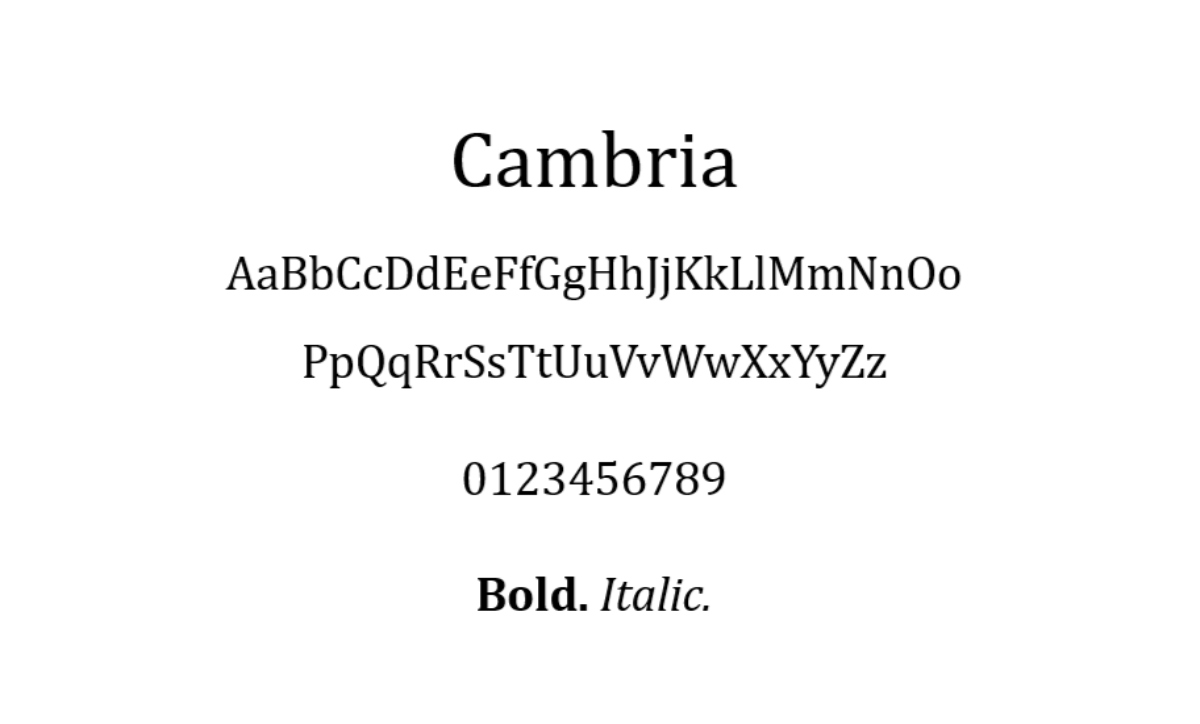
Con spaziatura e proporzioni molto costanti, Cambria è stato creato per un’eccellente lettura su schermo, anche quando visualizzato in piccole dimensioni. Troverai quattro diversi stili di questo font: regolare, grassetto, corsivo e corsivo grassetto.
Grazie ai graziati orizzontali in questo font, che enfatizzano fortemente le estremità di ogni tratto, è molto leggibile.
La versatilità di questo font è un’altra cosa che noterai. Il font può essere utilizzato per il corpo del testo, titoli e intestazioni combinando i suoi vari stili.
2. Arial
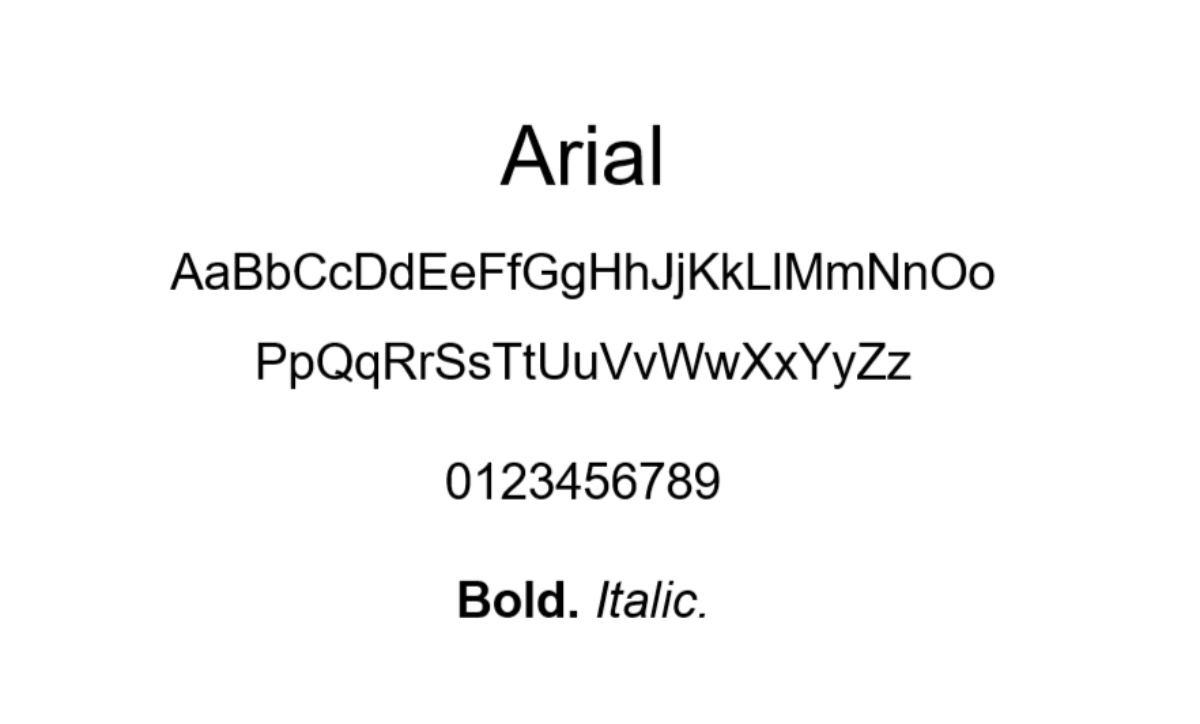
Con un’estetica moderna, Arial è un font sans-serif polivalente. La costruzione spessa e solida di ogni lettera crea un aspetto semplice e moderno.
Poiché Arial può essere letto a qualsiasi dimensione, è diventato un font standard per lo schermo. È persino diventato il font predefinito per Google Docs. Inoltre, questo font è ampiamente utilizzato in materiali stampati come pubblicità e giornali.
Arial è un’opzione fantastica se non stai cercando qualcosa di grande o elegante e vuoi semplicemente optare per un font tradizionale che funzionerà bene sulla maggior parte dei siti web.
3. Verdana
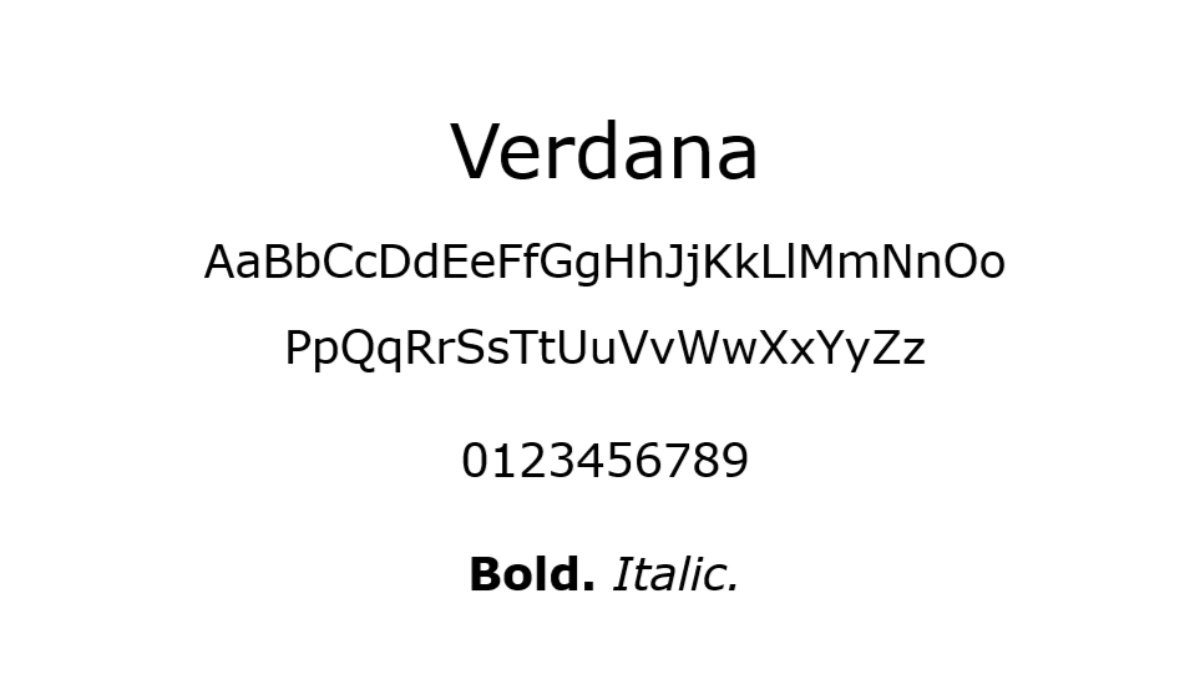
Verdana è un ottimo font per lo schermo perché può essere letto in piccole dimensioni e su schermi con bassa risoluzione. Questo è principalmente dovuto alla spaziatura ampia e alla larghezza dei caratteri.
Questo carattere non è solo per l’uso nella tipografia su schermo, però. Ad esempio, la nota azienda di mobili IKEA utilizza Verdana sia per i suoi cataloghi stampati che per il sito web.
Se stai cercando un font HTML con eccellente leggibilità, questo font è un’opzione fantastica
4. Perpetua
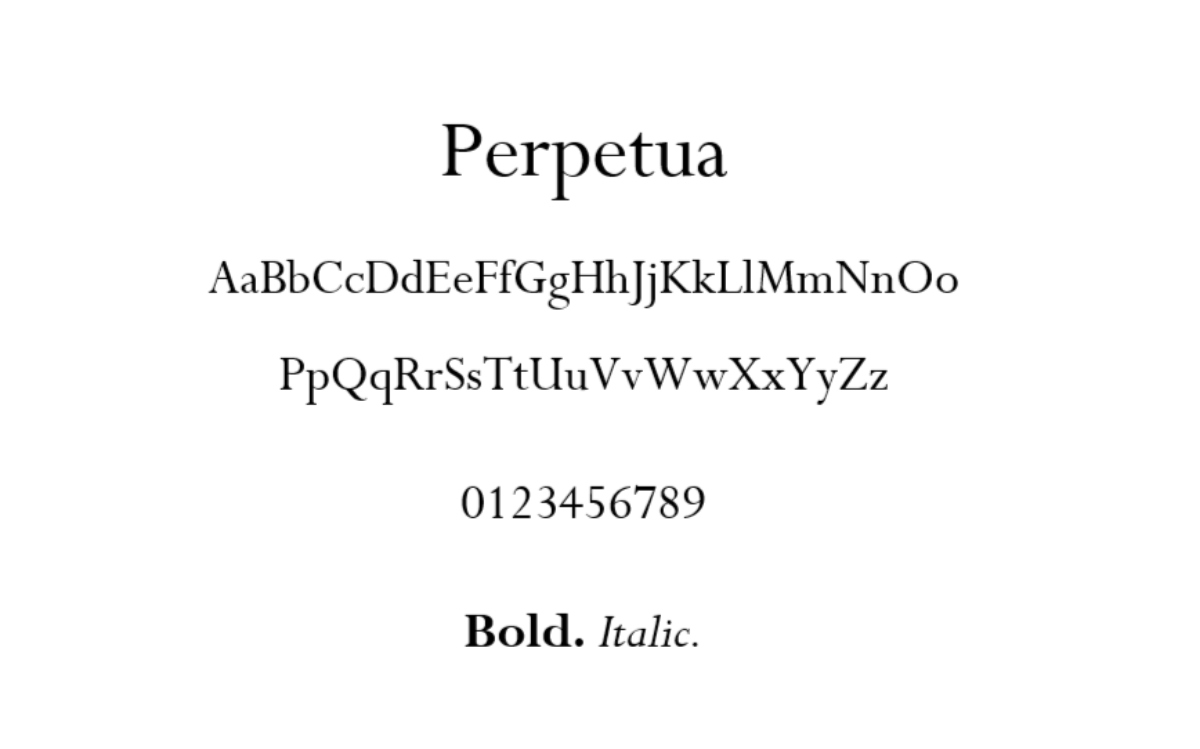
Perpetua è formale, senza tempo e raffinato. Uno scultore inglese che si è ispirato alle iscrizioni commemorative e ai monumenti ha sviluppato il font per la British Monotype Corporation.
Ancora di più, le qualità di questo font hanno ispirato l’Università della Pennsylvania e Penguin Classics a utilizzare Perpetua nelle loro pubblicazioni.
Nel complesso, questo font è molto utile per pagine e siti web educativi o informativi.
5. Brush Script
Se stai cercando qualcosa di informale e casual, allora Brush Script è un ottimo font script dall’aspetto moderno. Ha un design calligrafico basato sui metodi di scrittura. Ecco perché Brush Script MT è un font display stupendo ma leggibile per il tuo sito web.
Inoltre, questo font funziona bene per newsletter pop-up e landing page sui siti web. Considerando la natura dei suoi componenti, è meglio utilizzare questo font con parsimonia e in grandi dimensioni.
6. Monaco
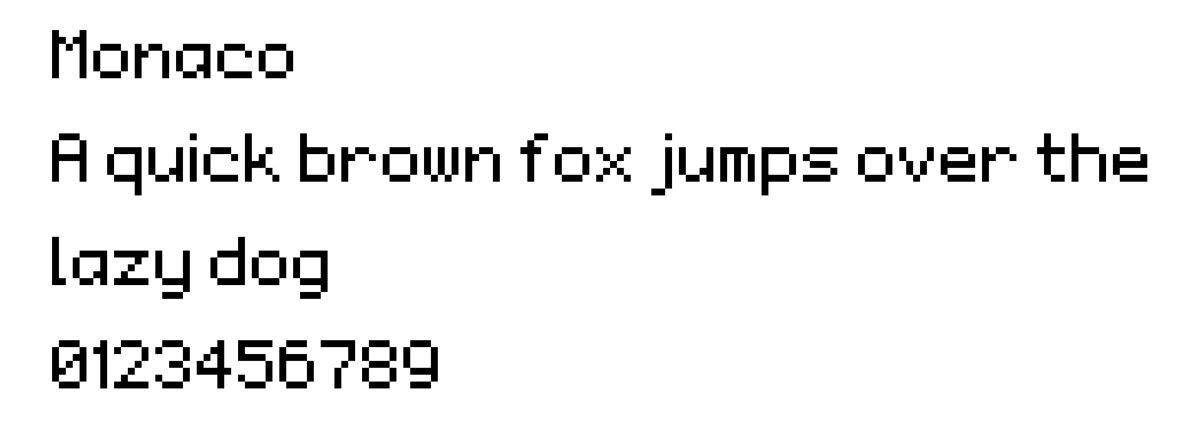
Se stai cercando un font utilizzato dalle applicazioni Xcode e Terminal su macOS X, allora Monaco è quello che stai cercando. Presenta un design pixelato ed enfatizzato che lo fa risaltare.
Monaco appare al meglio quando utilizzato come testo decorativo su layout di siti web dedicati alla codifica o al gaming grazie al suo design unico.
7. Candara
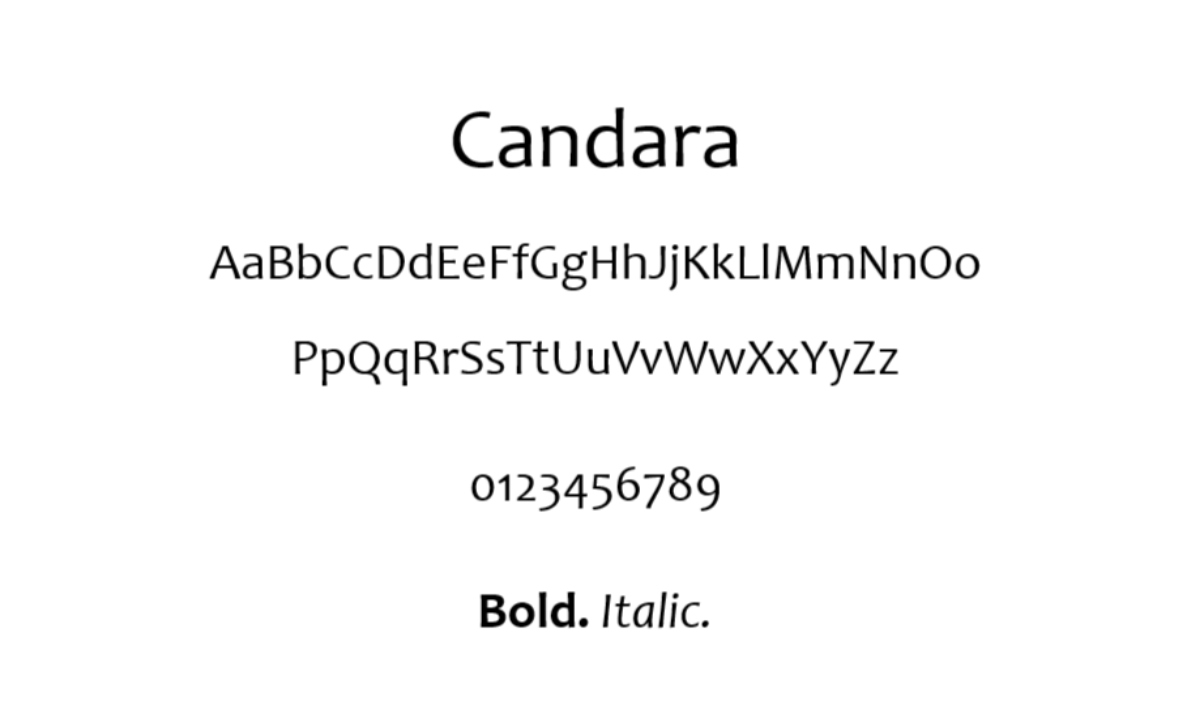
Il sistema operativo Microsoft Vista ha introdotto Candara al pubblico per la prima volta al fine di migliorare la leggibilità del display LCD. Questo carattere è ideale per i display grazie alla sua leggibilità e alla generosa spaziatura dei caratteri.
Inoltre, Candara ha un ottimo aspetto moderno grazie alle sue forme aperte e curve. Questo lo rende ottimo per impostazioni tipografiche casual come titoli di post di blog e slogan di siti web.
8. Courier
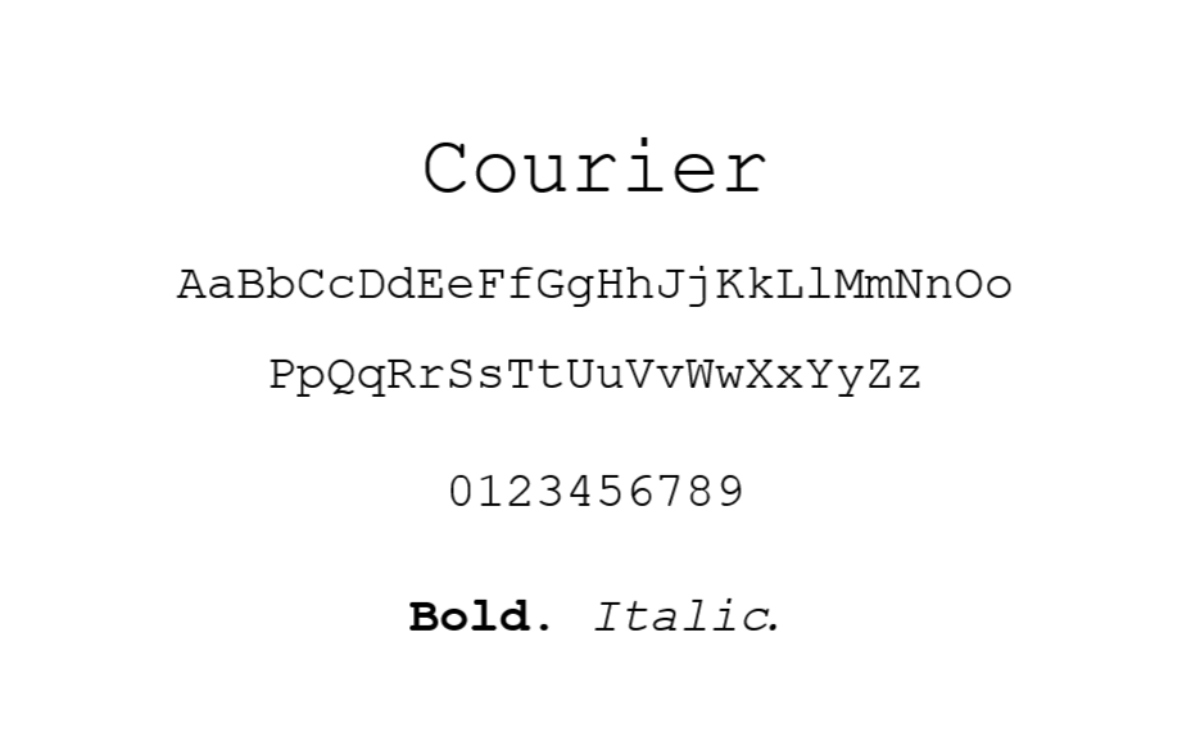
Il font serif slab più noto è Courier, che è incluso in tutti i sistemi operativi. Anche le sceneggiature per i film hanno utilizzato questo font HTML come standard.
Detto questo, dovresti considerare fortemente di includere Courier nel design del tuo sito se il tuo sito web ha qualcosa a che fare con i film. Ma, è meglio utilizzare questo font solo per intestazioni e titoli perché è classificato come decorativo.
9. Geneva
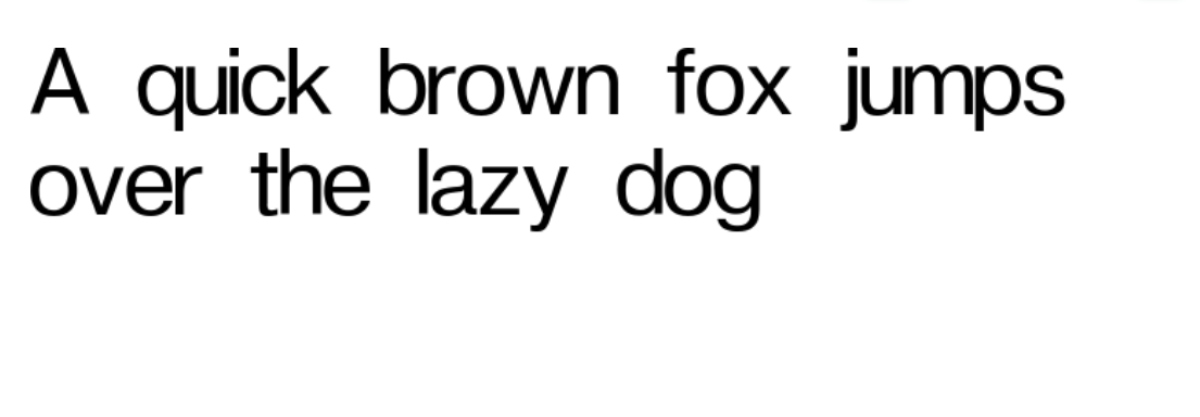
La larghezza, la spaziatura e la lunghezza uniformi di Geneva gli conferiscono un aspetto nitido e contemporaneo.
Sia il display che il corpo del testo utilizzano frequentemente questo font grazie alla sua flessibilità. Questo font è leggibile a qualsiasi dimensione grazie al suo stile classico e ai tratti sottili; fornisce anche una generosa spaziatura e una gamma di lunghezze di riga per garantire la leggibilità.
10. Arial Narrow
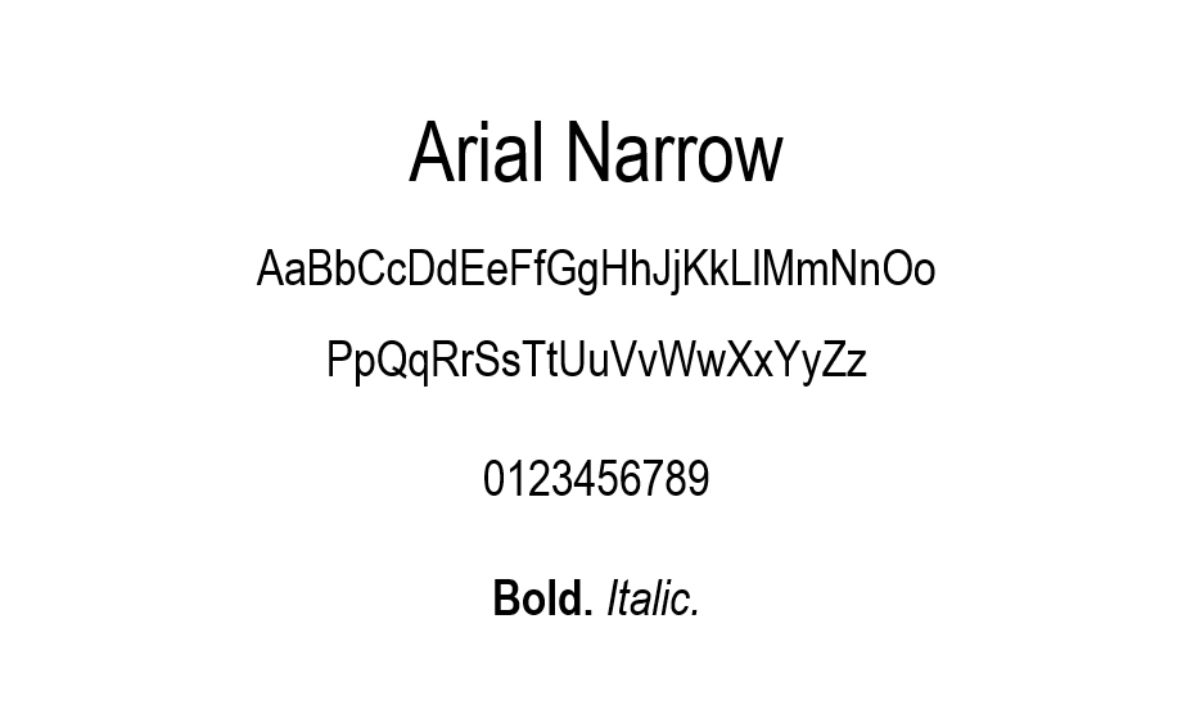
Delle 38 variazioni della famiglia di font Arial, Arial Narrow è una di queste. Questo carattere ha un design molto più snello che lo rende più unico rispetto all’originale. Un piccolo spazio separa le lettere, facendole apparire condensate e strette. Per questo motivo, Arial Narrow è un’opzione fantastica per siti web semplici.
Se vuoi abbinare altri font con Arial Narrow, i caratteri sans-serif più grassetti come Verdana e Geneva sono scelte fantastiche.
11. Optima
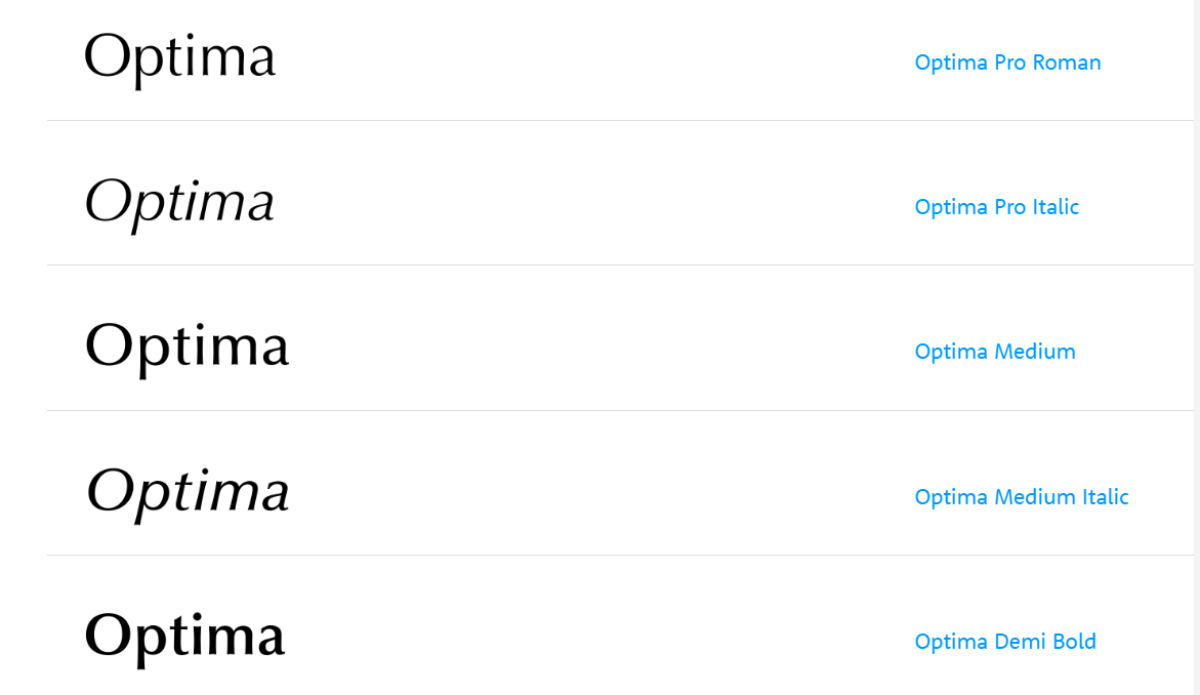
Optima trae ispirazione dalle lettere maiuscole dell’antica Roma. Con la sua ampia spaziatura e i tratti simmetrici, è utilizzato per trasmettere eleganza. Ciò che è anche ottimo è che puoi scegliere di specificare la distanza tra ogni carattere. Anche se tutte le opzioni di spaziatura sono leggibili, allargare la spaziatura si adatterà meglio a questo font.
Come si vede nei loghi di aziende di fascia alta come Marks and Spencer ed Estée Lauder, Optima è ideale per l’uso display.
12. Calibri
Un carattere comune e molto apprezzato è Calibri. È il font predefinito per una serie di programmi ben noti, incluso il pacchetto Microsoft Office e Google Docs. Grazie ai suoi bordi arrotondati e al design semplice, questo font trasmette principalmente una sensazione moderna e accogliente.
Calibri funziona anche bene in una vasta gamma di dimensioni di testo. Questo lo rende adatto per display digitali e schermi ed è molto leggibile.
Con il suo design semplice, può essere utilizzato praticamente per qualsiasi sito web.
13. Garamond
Se stai cercando un font serif in stile antico, allora Garamond è la scelta perfetta. È uno stile di font tradizionale che viene frequentemente utilizzato in display stampati e digitali, come i libri di Harry Potter, il logo di Google e la serie di libri del Dr. Seuss.
Questo font è ideale per dare al tuo sito web un’atmosfera vintage ma classica.
14. Didot
Il font neoclassico Didot ha un design tradizionale con un tocco contemporaneo. Se hai bisogno di un font display per le intestazioni, gli slogan o i titoli sul tuo sito web, allora questa è un’ottima scelta. Grazie al suo alto contrasto e all’accento aggiunto, questo carattere è noto per risaltare.
Inoltre, il Late Show con Stephen Colbert e CBS News utilizzano entrambi il font distintivo.
15. Playfair Display
Il font serif Playfair Display ha un’atmosfera piacevolmente moderna con un accenno di femminilità.
Questo carattere è la scelta ideale per siti web che si rivolgono alle donne. Il peso di un font è inversamente correlato a quanto sia esteticamente gradevole. In altre parole, più leggero è il font, più è piacevole da guardare per design.
Quali Sono i Principali Tipi di Font?
Progettare il tuo sito web con il miglior font è come scegliere il colore perfetto per dipingere la tua casa. La nuova mano di vernice rinfrescherà la tua casa e rivelerà molto sulle persone che ci vivono, quindi vuoi fare la scelta giusta. Una casa con vernice che si sta scrostando indica trascuratezza, mentre una con colori lucidi e vibranti mostra una buona manutenzione.
Allo stesso modo, proprio come i colori fanno per una casa, i font sono usati per evocare emozioni particolari e forgiare associazioni speciali nella mente con un particolare marchio. Quando progetti un sito web, dovresti considerare i vantaggi, gli svantaggi e le connotazioni psicologiche di ogni tipo di font.
Ci sono quattro tipi principali di font, e ciascuno è collegato a un’emozione diversa. È cruciale che il font che scegli supporti l’obiettivo del tuo sito web, proprio come fa con ogni altro componente. I seguenti sono i quattro diversi tipi di font e ciò che trasmettono:
- Serif Se vuoi proiettare un marchio sofisticato ed elegante, i font serif sono un’opzione ottima e popolare da scegliere. Danno al tuo sito web un’atmosfera tradizionale, rispettabile e affidabile.
- Sans-serif Questi font forniscono un aspetto semplice e ordinato. Grazie al loro design elegante ed efficace, possono essere audaci e utilizzati come attira-attenzione pur enfatizzando chiarezza e un approccio lungimirante. I siti web che scelgono questa famiglia di font attribuiscono un alto valore all’onestà e alla sensibilità che non richiedono nulla di fantasioso o non necessario.
- Script Tipicamente, i font script appaiono sotto forma di femminilità, creatività, eleganza e libertà. Trasmettono un approccio più pratico e individuale ai siti web attraverso i loro stili curvi e fioriti. Utilizzare efficacemente i font script può aiutare i siti web a esprimere un senso di “tocco personale” e pensiero artistico.
- Display Questi font tendono a enfatizzare l’originalità e trasmettere unicità. Inoltre, grazie alla loro adattabilità, i siti web possono combinare e contrastare vari stili di font per scegliere quali emozioni enfatizzare. Un senso di divertimento, pensiero casual e creativo sono alcune delle sensazioni più frequenti evocate dai font display.
Detto questo, assicurati che i font che scegli per il tuo sito web siano esteticamente gradevoli e unici per te. Questo serve per rappresentare efficacemente il tuo marchio su tutte le piattaforme e i browser.
Per fortuna, con i costruttori di siti web, rendono semplice anche per i principianti applicare i font sul tuo sito web. Praticamente chiunque può progettare un sito web al giorno d’oggi grazie all’aiuto di funzionalità semplici come la funzionalità drag-and-drop. Con pochi clic, i migliori hosting web rendono anche molto facile configurare un sito web.
La Scelta del Font Web è Importante?
Si dice che una prima impressione sia difficile da cancellare, e i font sul tuo sito web rivelano già molto su di te. Poiché è una delle prime cose che i tuoi visitatori noteranno quando arrivano, il font sul tuo sito web può effettivamente avere un impatto sulla decisione dei visitatori di rimanere o andarsene.
Una scelta sbagliata di font può dare al tuo sito web un aspetto economico e non professionale, che si rifletterà negativamente sulla tua attività.
I font ideali sono leggibili, alla moda e supportano l’identità del tuo marchio. Ma mentre scegliere un font che esprima la tua personalità e l’identità del marchio è una buona idea, dovresti anche evitare di esagerare con design troppo carini o complessi. Ad esempio, cose come un font eccessivamente stilizzato possono rendere difficile la lettura del tuo testo, potenzialmente frustrando il tuo pubblico e facendoli uscire dal tuo sito.
Ora che sei consapevole di alcuni da fare e da non fare, passiamo ad alcuni stili di font, ok?
Gli Stili dei Font Sono Una Parte Importante dell’Identità del Tuo Sito!
Una parte cruciale di qualsiasi identità di marca è selezionare il font giusto. Quello ideale può aiutarti a comunicare più efficacemente i valori e gli obiettivi della tua azienda aggiungendo nuovi strati di simbolismo al tuo marchio.
Tuttavia, tieni sempre a mente come ogni stile di font e carattere supporta l’aspetto e la sensazione del tuo marchio. Il tuo marchio può raccontare la storia della tua azienda nel modo in cui era destinata a essere raccontata trovando la giusta combinazione di tipi ed elementi di design.
Quindi, ora che conosci i migliori font da utilizzare, vai avanti e progetta il sito web perfetto!